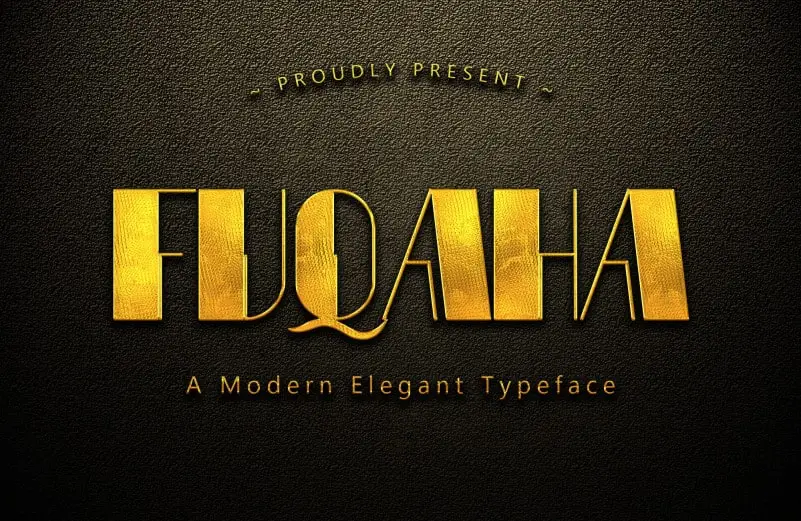
A Fuqaha Display Font é uma tipografia forte e moderna, criada pelo designer Alfatih Std. Esta elegante e robusta fonte se destaca tanto para aplicações do cabeçalho quanto para texto, proporcionando um ar futurista e tecnológico. Suas linhas estilizadas parecem flutuar no espaço digital, invocando atmosferas de robôs, androids, alta tecnologia, futuro e realidade virtual. Suas cores vibrantes também a tornam perfeita para aplicações em áreas como a armada e jogos. Seu design atemporal e inovador também é adequado para ambientes que valorizam a eficácia no design gráfico moderno, projetando uma atmosfera de alta tecnologia e criatividade futurista. A Fuqaha Display Font se destaca como uma excelente opção quando você deseja transmitir uma imagem tecnologicamente avançada em seus projetos digitais. Com seu estilo audacioso e estilizado, esta fonte é ideal para destacar qualquer design que precise de um apelo moderno e futurista. Aproveite o poder da Fuqaha Display Font para dar vida aos seus projetos de design gráfico, criando ambientes visuais atemporais e imprevisíveis.